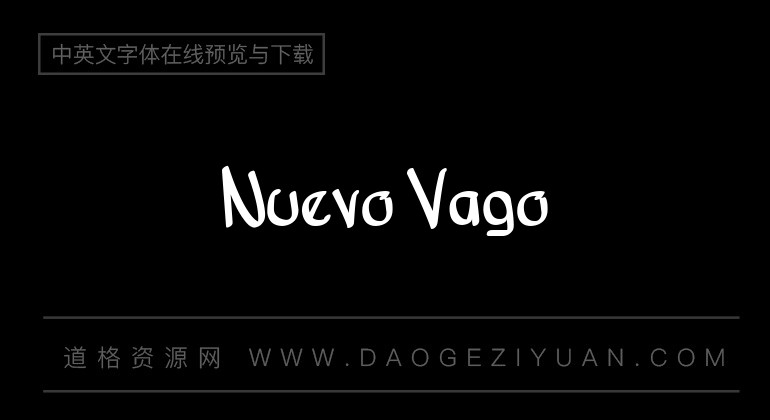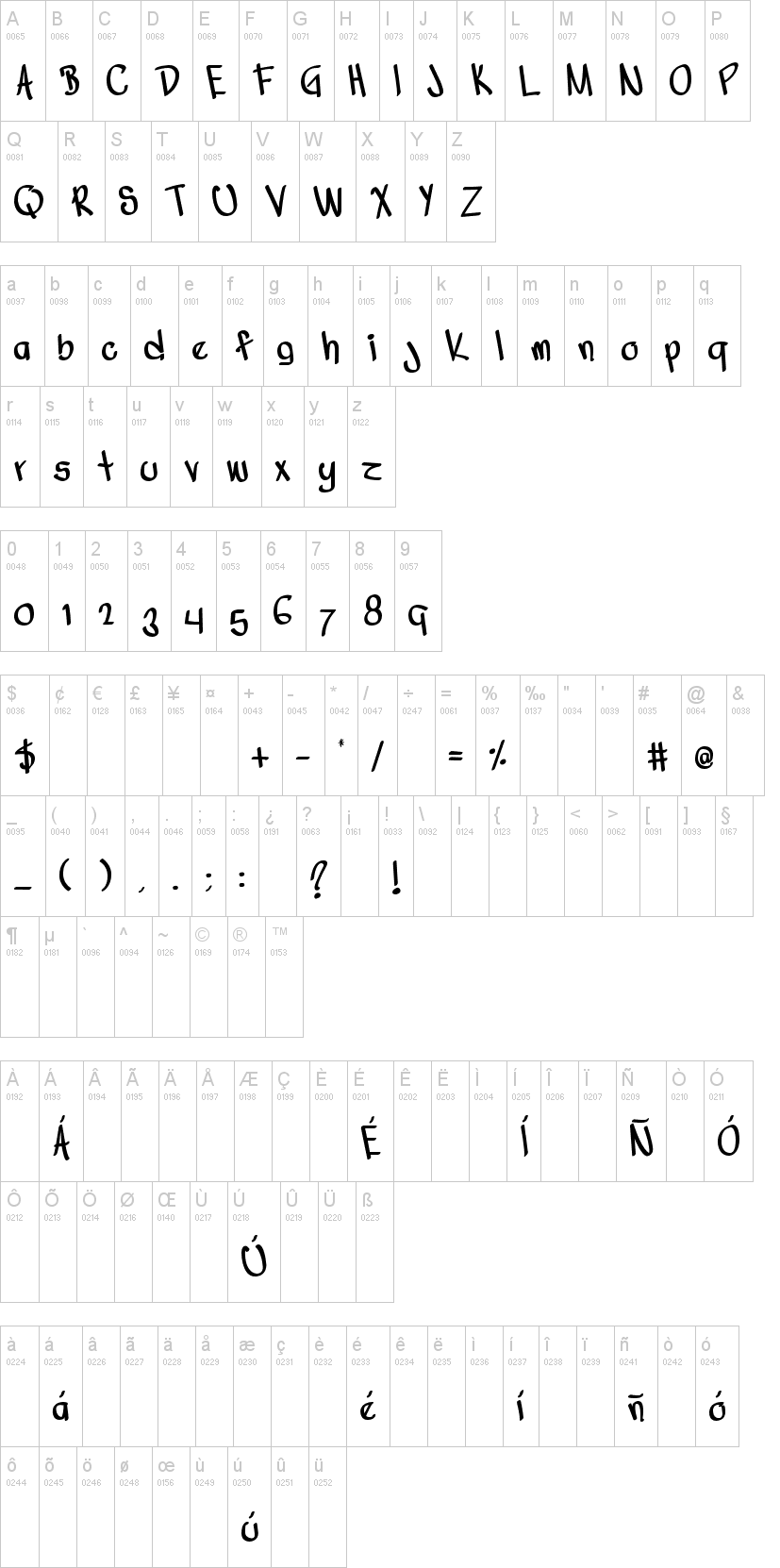
Nuevo Vago是一款新潮的墨西哥风格字体,它具有粗犷、自然、活泼的特点,可以用于现代设计中的文字和图形。Nuevo Vago的字形具有清晰的轮廓,笔画粗细均匀,让您的文字充满活力。它的特点是简洁、紧凑,可以提供优秀的可读性,同时又具有独特的现代风格。它可以用于品牌标识、海报、包装、T恤、网页、报纸和杂志等等,可以满足您的各种设计需求。内容介绍
Nuevo Vago是一款非常不错的手写艺术字体,具有很好的视觉感,适合于文化类的宣传设计、商业类品牌的广告和产品包装设计以及个性化文字排版等较多场景。